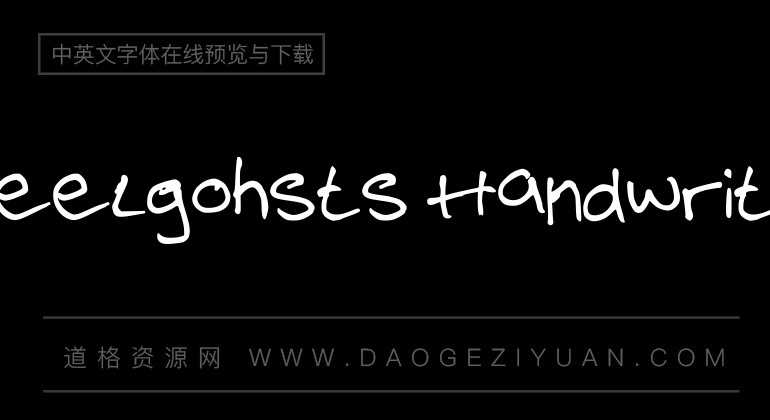
Steelgohsts Handwriting
Steelgohsts Handwriting 是一款手写字体,由设计师 Steelgohsts 创作。它采用了经典的手写风格,具有温暖、舒适的感觉,可以为您的文字添加一份特别的情感。该字体包含多种字符,可以满足您的不同需求。它的笔画细腻,字形简洁,是一款优秀的手写字体。
Steelgohsts Handwriting是一款非常不错的手写艺术字体,具有很好的视觉感,适合于文化类的宣传设计、商业类品牌的广告和产品包装设计以及个性化文字排版等较多场景。